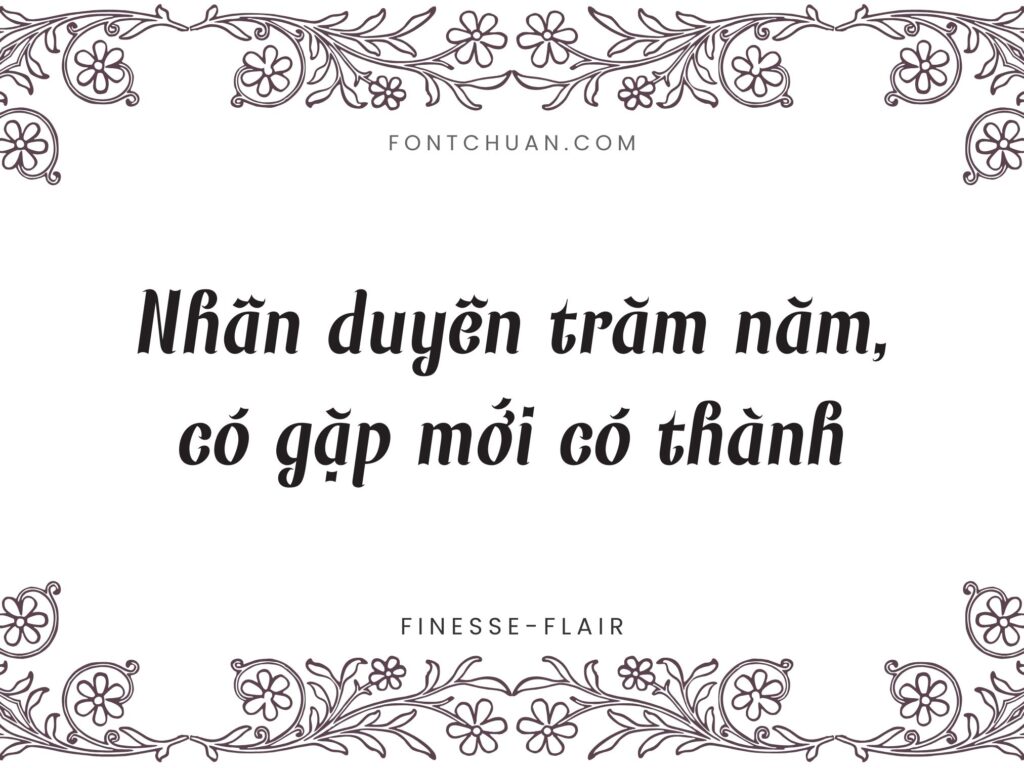
Font Finesse Font Tiếng Việt
Finesse là một font chữ script được thiết kế bởi Behalf Studio, lấy cảm hứng từ chữ viết tay nghiêng trên xe sửa đồng hồ của nghệ nhân Hoài Minh Phương. Font này mô phỏng phong cách và đặc trưng của nghệ nhân, tôn vinh nét đẹp thủ công trong kiểu chữ Việt Nam. Finesse bao gồm 5 biến thể: Roman, Italic, Flair, Future và Oblique, hỗ trợ đầy đủ tiếng Việt và nhiều ngôn ngữ khác. Font được sưu tầm và đăng bởi thành viên của Font Chuẩn.
Font có thiết kế chữ mềm mại với sự tương phản giữa các nét mỏng và dày, tạo nên sự thanh lịch và tinh tế. Finesse phù hợp cho các thiết kế như thiệp mời, logo, tiêu đề và các ấn phẩm truyền thông cần sự sang trọng và chuyên nghiệp. Các ngành nghề như quảng cáo, thiệp cưới, spa và giáo dục có thể tận dụng hiệu quả font này. Ngoài ra, Finesse cũng thích hợp cho các sự kiện như lễ hội, sinh nhật, ngày Nhà giáo và Valentine.
Đặc biệt, Finesse còn là lựa chọn lý tưởng làm font chữ spa, giúp các thương hiệu chăm sóc sức khỏe, làm đẹp hay spa thể hiện sự tinh tế, thanh lịch và chuyên nghiệp trong từng thiết kế. Dù là trên bảng hiệu, tờ rơi, brochure hay các bài đăng mạng xã hội, font này vẫn giữ được vẻ mềm mại, uyển chuyển và sang trọng. Sự kết hợp giữa Finesse và môi trường spa không chỉ nâng cao thẩm mỹ mà còn tạo cảm giác thư giãn, dễ chịu cho khách hàng, đồng thời thể hiện phong cách riêng biệt và đẳng cấp của thương hiệu.